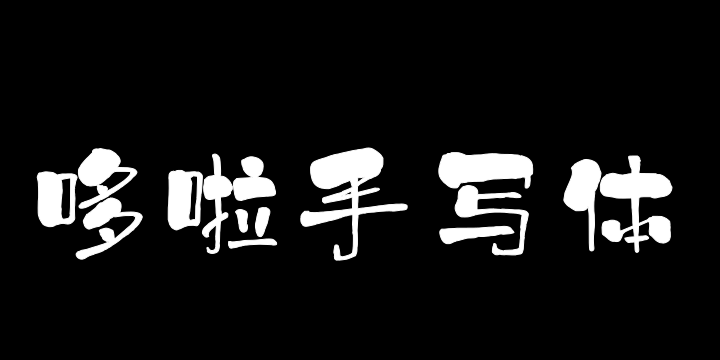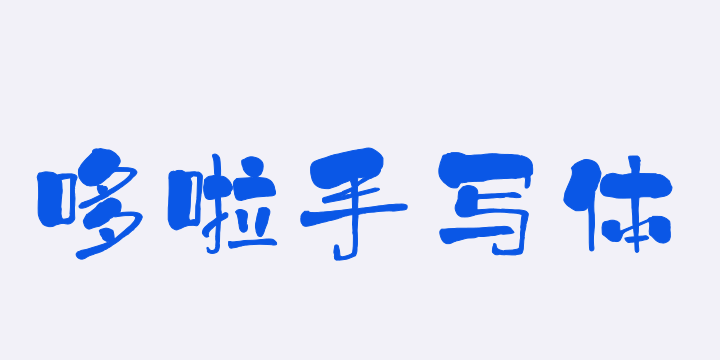
上首哆啦手写体 By 上首造字 商用字体
字体全名: 上首哆啦手写体
铸字厂: 上首造字
设计师: 胡博剑
字体简介: 上首哆啦手写体,简体中文约6763字。这套字体以古朴韵味为底色,融入现代萌趣设计理念重塑字形。将起笔 “蚕头” 简化为圆润小顿角,收笔 “燕尾” 弱化尖锐形态,转为柔和的短弧收尾,让笔画既存隶书韵味,又添憨态。竖画、撇捺等笔画适度加粗、截断,如竖画末端以利落平切收笔,制造 “积木块” 般的稚拙感,使字体线条在古朴中透出灵动。